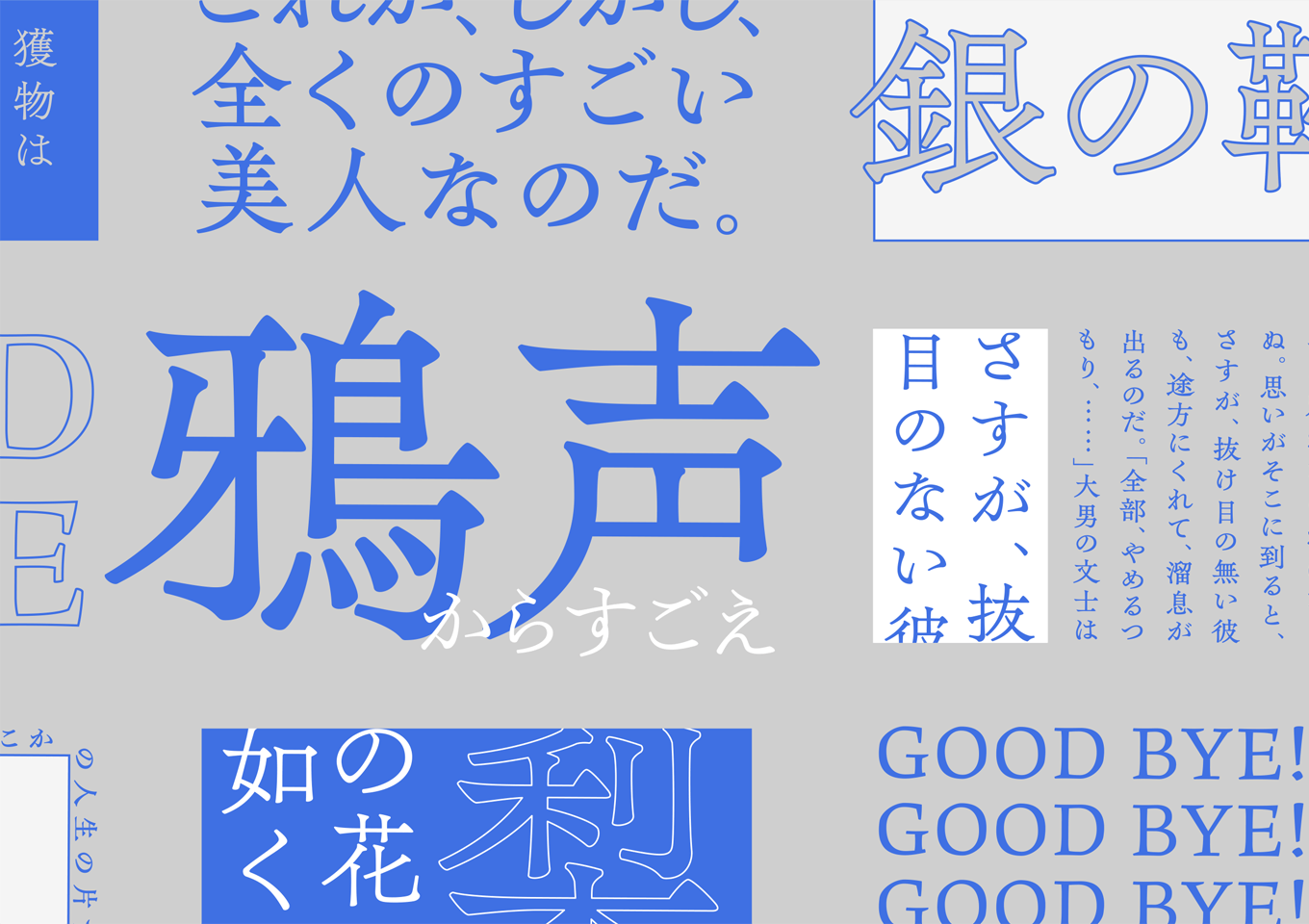
楷書体の要素を色濃く残すローコントラストなオールドスタイルの明朝体です。横線やハライの伸びやかさを強調したふところの締まった骨格の漢字に、1940〜60年代の活字にインスパイアされたかなを合わせました。欧文は15世紀末の活字の骨格をベースに、無骨さを強調したデザインに仕上げています。文芸雑誌や広告の見出しなどで、クラシックな印象を与えたい際に最適です。
Min2
L / R / M / B
楷書体の要素を色濃く残すローコントラストなオールドスタイルの明朝体です。横線やハライの伸びやかさを強調したふところの締まった骨格の漢字に、1940〜60年代の活字にインスパイアされたかなを合わせました。欧文は15世紀末の活字の骨格をベースに、無骨さを強調したデザインに仕上げています。文芸雑誌や広告の見出しなどで、クラシックな印象を与えたい際に最適です。
Min2
L / R / M / B